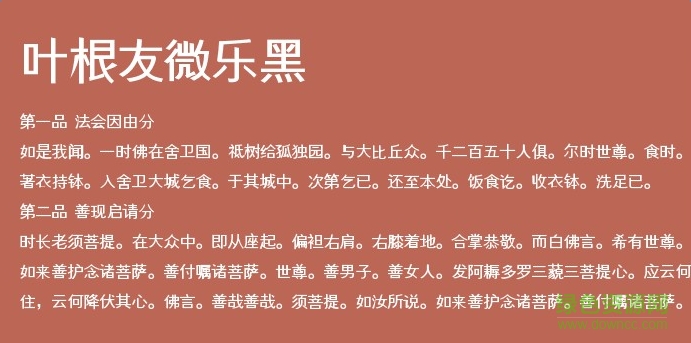
葉根友微樂黑字體是一款簡約黑風(fēng)格字體軟件,微樂黑體是微黑系列中比較活潑開朗的一款字體,字體一筆一畫一絲不茍,粗細均勻,耐看性十足,還有更多好看字體歡迎來綠色資源網(wǎng)下載體驗!
葉根友微樂黑是一款渾厚印刷體,可用于內(nèi)文排版或者標(biāo)題用字,時尚的黑體風(fēng)格,干凈而不失大氣的字體筆畫。
該字體橫豎相間,沒有一絲多余的彎曲,整體性十分震撼,藝術(shù)氣息十足,是一款值得收藏的字體!